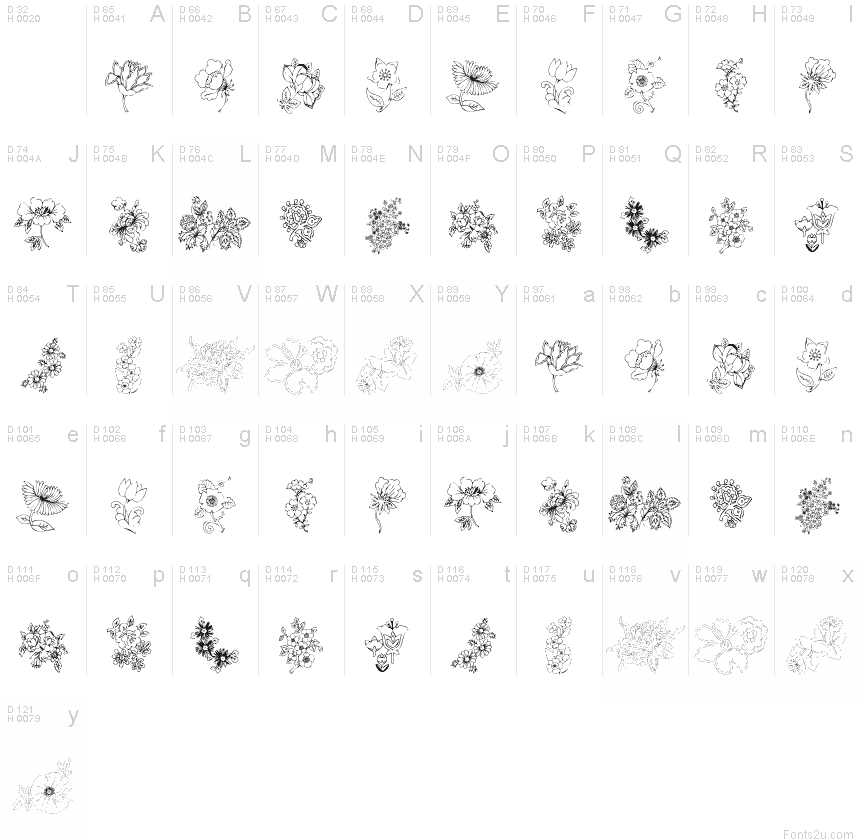
KR Floral Color Me 2 von Katsfunfonts ist eine kostenlose florale Dingbat-Schrift, die jeden Tastendruck in eine detailreiche Gartenillustration verwandelt. Jedes Motiv wirkt wie eine handgezeichnete Malvorlage: klare Konturen, geschwungene Blütenblätter, geschichtete Blätter und kleine Beeren, die dazu einladen, sie mit Farbe zu füllen oder sie als filigrane Strichzeichnung stehen zu lassen. Die Zeichnungen sitzen sauber auf der Grundlinie, sodass sich Rahmen, Muster und kleine Illustrationen mühelos ausrichten lassen.
Mit KR Floral Color Me 2 verleihen Sie Grußkarten, Malvorlagen, Scrapbook-Seiten, Einladungen, Planern und Verpackungen im Handumdrehen illustrierte Akzente. Diese kostenlose Schrift kommt besonders in großen Größen zur Geltung, wo die feinen Linien und Schwünge atmen können. Kombinieren Sie sie für den Fließtext mit einer klaren, zurückhaltenden serifenlosen Schrift, damit die kunstvollen Blumen voll zur Geltung kommen.